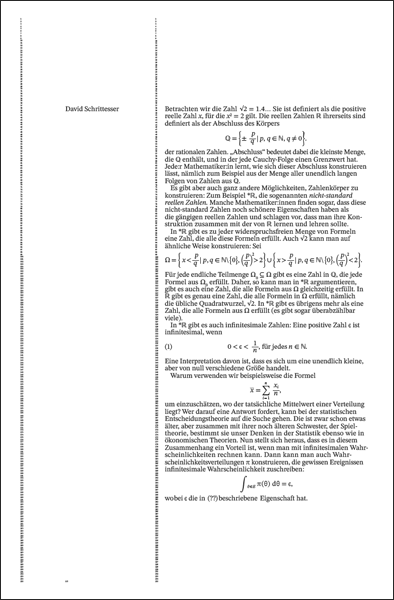
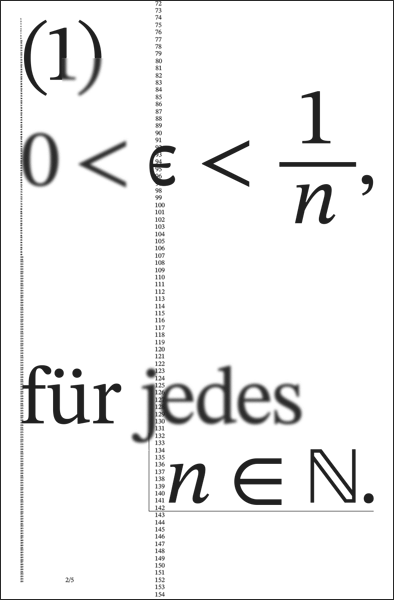
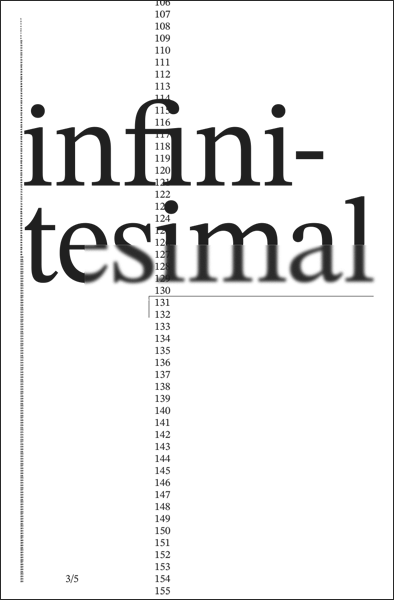
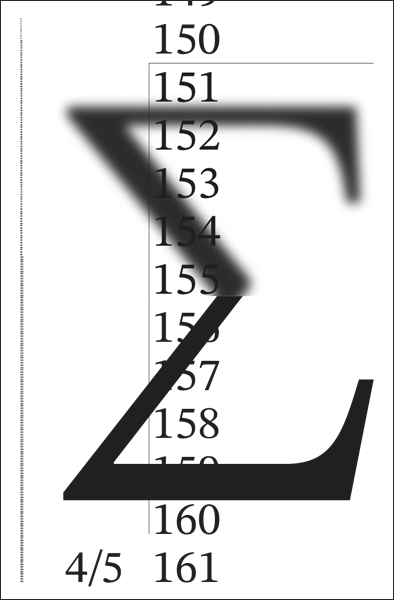
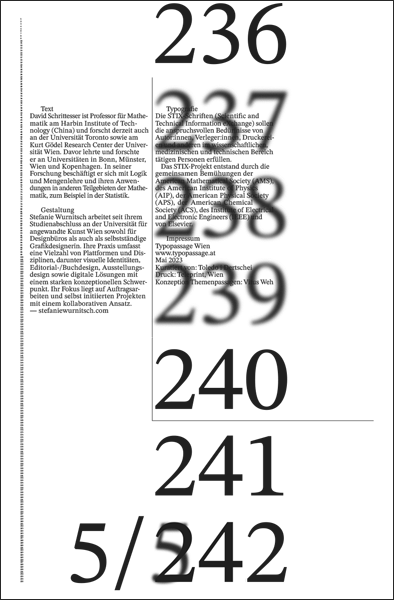
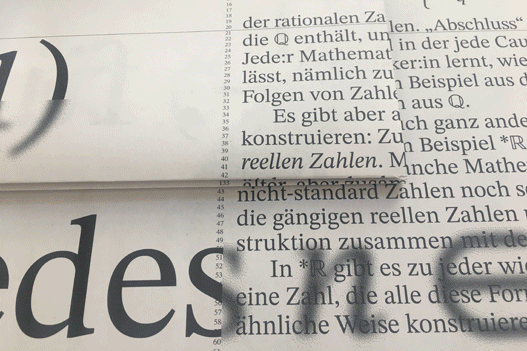
Typografie
Die STIX-Schriften (Scientific and Technical Information eXchange) sollen die anspruchsvollen Bedürfnisse von Autor:innen, Verleger:innen, Druckereien und anderen im wissenschaftlichen, medizinischen und technischen Bereich tätigen Personen erfüllen. Das STIX-Projekt entstand durch die gemeinsamen Bemühungen der American Mathematical Society (AMS), des American Institute of Physics (AIP), der American Physical Society (APS), der American Chemical Society (ACS), des Institute of Electrical and Electronic Engineers (IEEE) und von Elsevier.